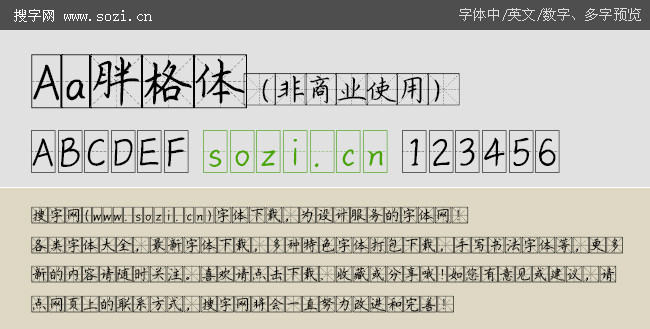
Aa胖格體
搜字網(wǎng)給大家提供一款A(yù)a胖格體(非商業(yè)使用)中文字體下載,該字體是一款手寫風(fēng)格的字體,字體筆觸適中,字形端正,每一個(gè)字體都在田字格中,具有很好的視覺(jué)感,清新簡(jiǎn)明,適用于平面宣傳設(shè)計(jì)、網(wǎng)頁(yè)設(shè)計(jì)、海報(bào)設(shè)計(jì)等應(yīng)用(此字體為個(gè)人非商用版,商用可以聯(lián)系QQ:1006760504)。